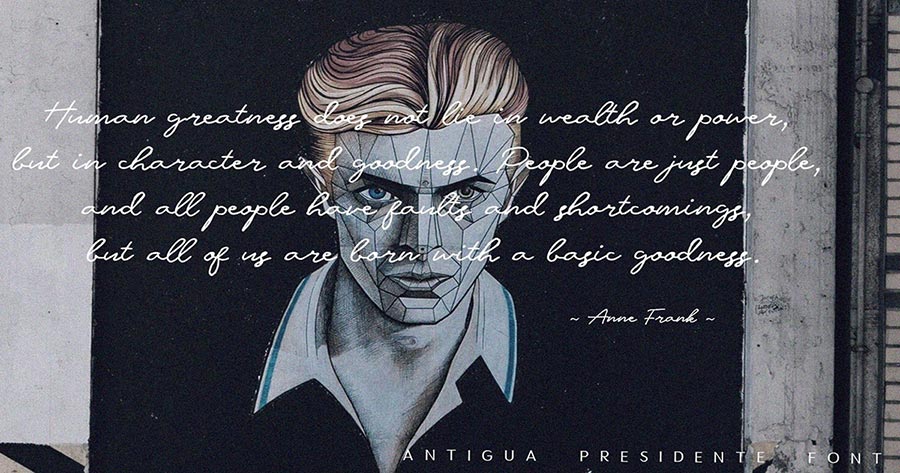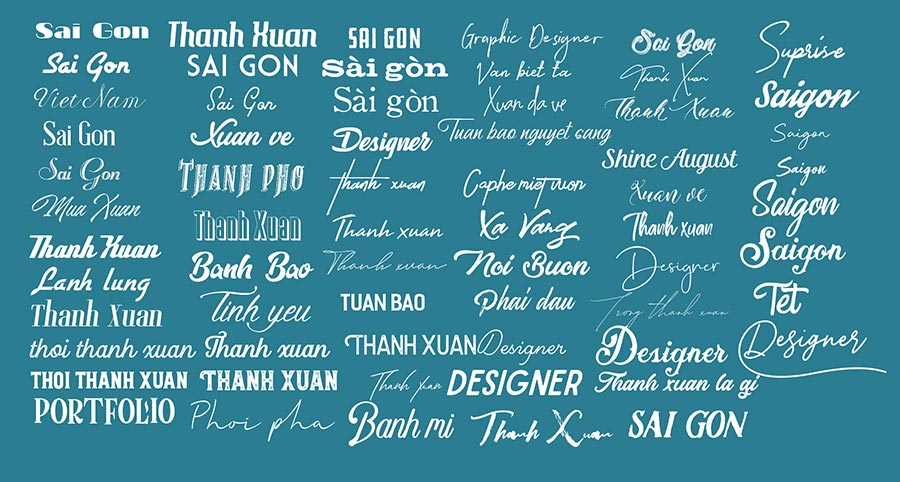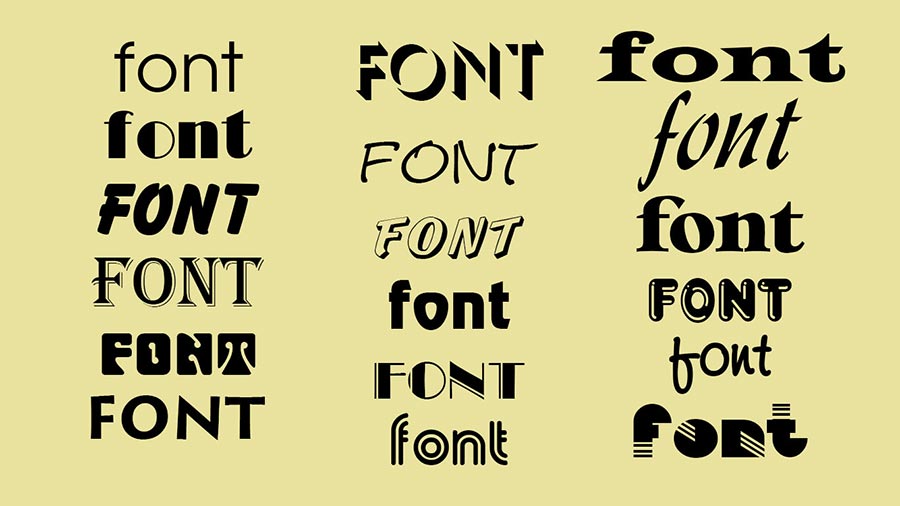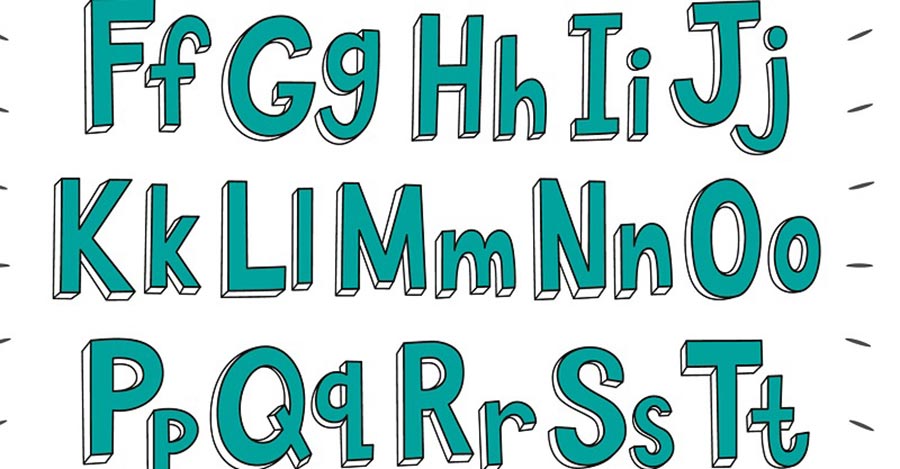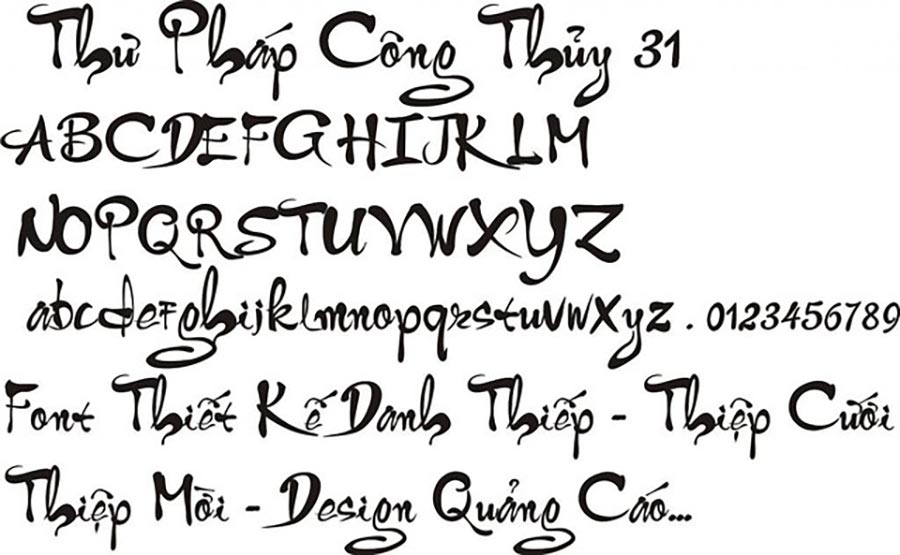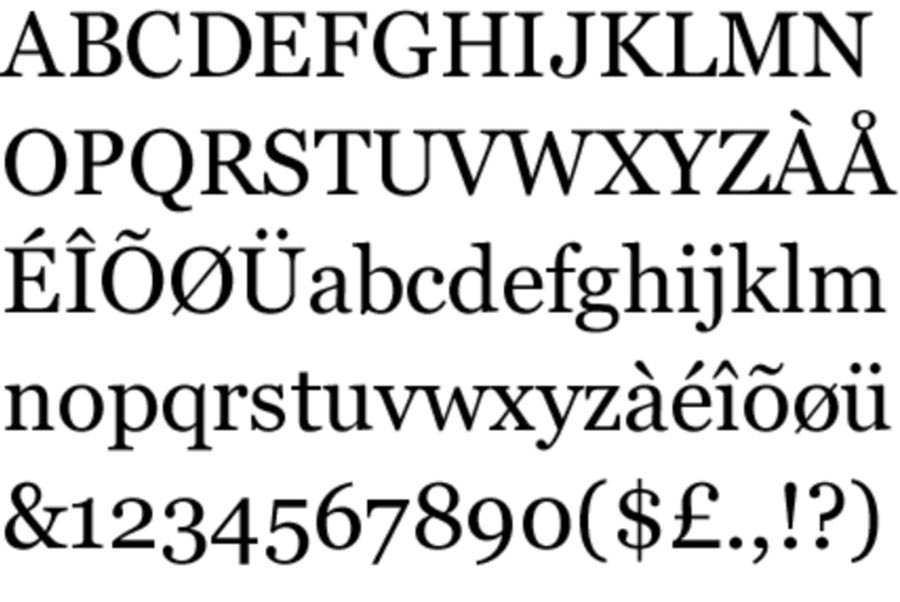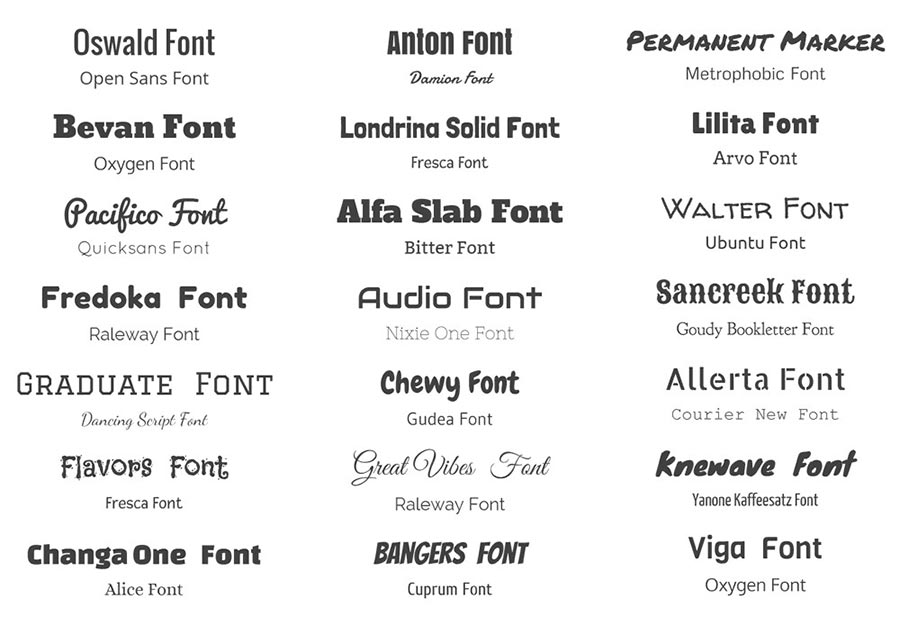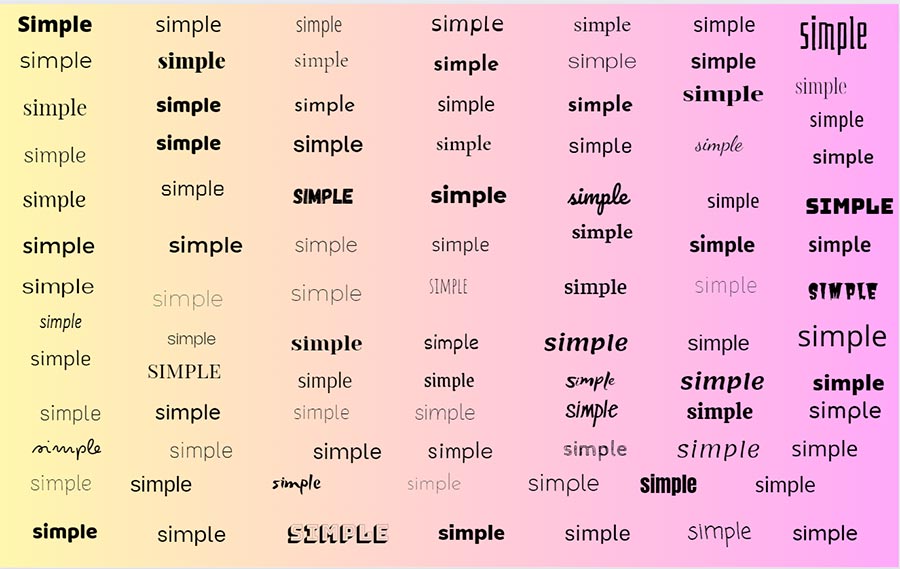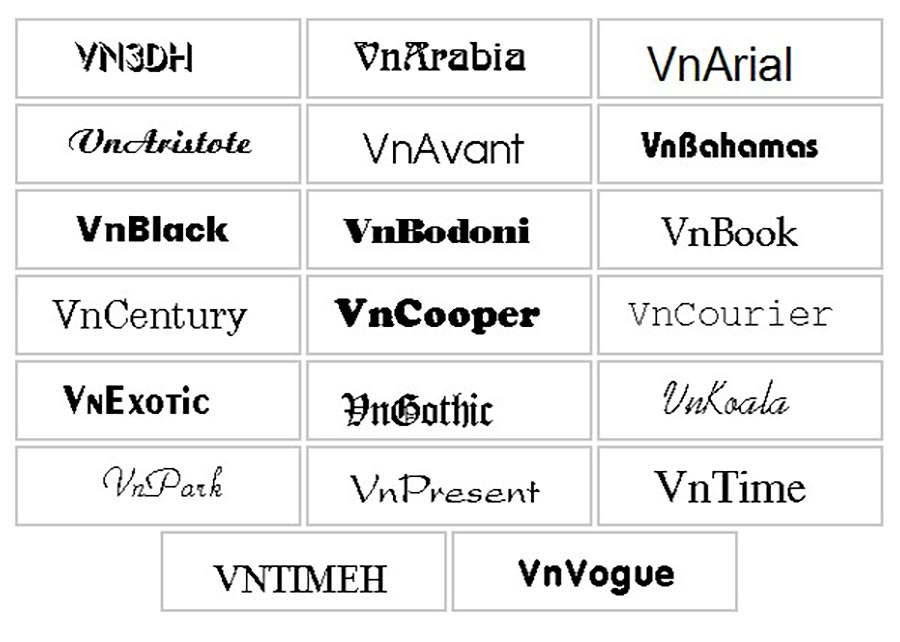
Chia Sẻ Miễn Phí 15+ Font Chữ Tổng Hợp Cực Đẹp
Nếu bạn là một designer đang tìm kiếm những font chữ chất lượng để làm phong phú thêm các dự án thiết kế của mình, thì bộ sưu tập 15+ Font Chữ Tổng Hợp Cực Đẹp từ Sadesign.vn chắc chắn là lựa chọn lý tưởng. Đây là bộ font miễn phí, dễ sử dụng và phù hợp với nhiều thể loại thiết kế khác nhau, giúp bạn dễ dàng tạo nên những sản phẩm ấn tượng và chuyên nghiệp.
Đặc Điểm Nổi Bật Của Bộ Font Chữ Tổng Hợp
• Đa dạng phong cách: Bộ sưu tập này bao gồm nhiều kiểu font chữ khác nhau, từ các font chữ hiện đại, cổ điển đến những font nghệ thuật, giúp bạn dễ dàng chọn lựa theo yêu cầu của dự án.
Các Font Chữ Tổng Hợp Cực Đẹp Dành Cho Mọi Thiết Kế
Bộ 15+ Font Chữ Tổng Hợp miễn phí của Sadesign.vn được thiết kế để đáp ứng nhu cầu của mọi loại hình thiết kế. Dưới đây là một số font nổi bật mà bạn có thể sử dụng trong các dự án của mình:
Font Chữ Thời Trang (Fashion Fonts)
Nếu bạn đang thiết kế các sản phẩm liên quan đến thời trang, bộ font chữ thời trang này sẽ là sự lựa chọn hoàn hảo. Với các đường nét thanh thoát, mềm mại nhưng cũng đầy cá tính, chúng sẽ giúp các thiết kế của bạn trở nên nổi bật và sang trọng hơn.
Font Chữ Viết Tay (Handwritten Fonts)
Font chữ viết tay tạo cảm giác gần gũi và tự nhiên, rất phù hợp cho các dự án thiết kế liên quan đến thiệp mời, thư chúc mừng, hoặc những sản phẩm cần sự nhẹ nhàng, dễ chịu. Font chữ này sẽ giúp bạn tạo ra những thiết kế tràn đầy cảm hứng và sự tươi mới.
Font Chữ Đậm và Mạnh Mẽ (Bold Fonts)
Dành cho những thiết kế cần sự nổi bật và mạnh mẽ, font chữ đậm với đường nét sắc nét sẽ thu hút sự chú ý ngay từ cái nhìn đầu tiên. Bạn có thể sử dụng chúng trong các poster, logo, hoặc banner quảng cáo để tạo ấn tượng mạnh mẽ.
Font Chữ Nghệ Thuật (Artistic Fonts)
Nếu bạn đang tìm kiếm những font chữ mang tính nghệ thuật, sáng tạo, bộ font nghệ thuật này sẽ mang đến cho bạn những lựa chọn tuyệt vời. Đặc biệt phù hợp cho các dự án quảng cáo nghệ thuật, album, hoặc thiết kế sản phẩm sáng tạo.